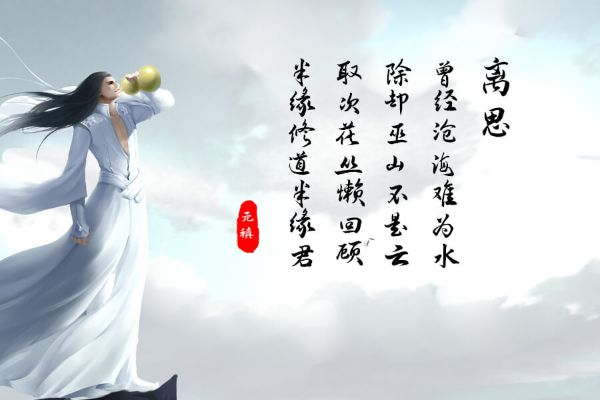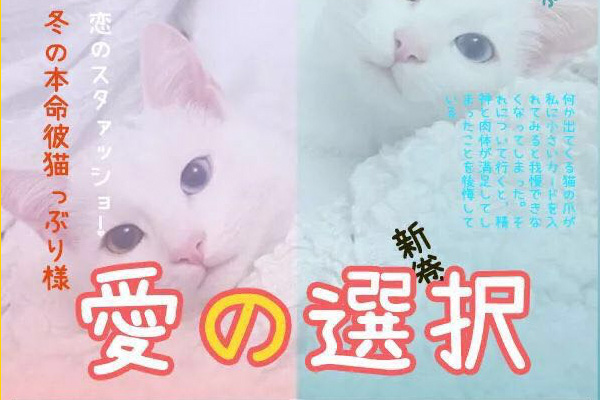
行楷字体可以商用吗?分享5款可以免费商用的行楷字体
什么是行楷字体?
介于楷书和行书之间的书写风格,就是行楷。字迹流畅又端正,既不像楷书那样一笔一画太慢,也不像草书那样难以辨认。
免费商用的行楷字体有哪些?
三极行楷简体
三极行楷简体笔画既有楷书的端庄,又融入了行书的流动感。线条粗细适中,笔锋处理较为圆润且有力。相比于过于草率的行书,这款字体的结构非常严谨,识别度很高,适合长文本阅读或副标题。
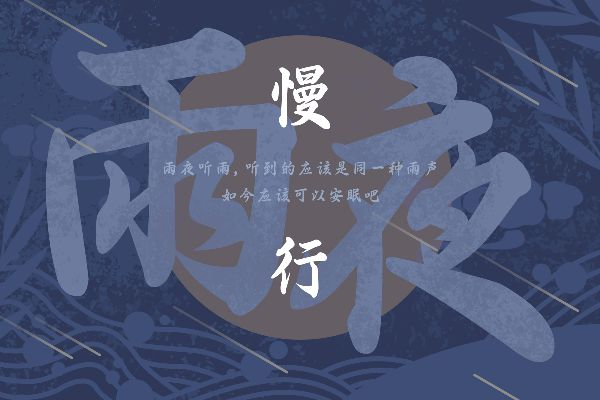
演示夏行楷
演示夏行楷保留了真实毛笔书写的韵味,笔划连绵,富有动感,甚至带有一些“江湖气”和洒脱感。字形结构舒展,视觉冲击力比普通行楷更强,非常适合作为大标题使用。
濑户字体
濑户字体是一款日本开源字体,包含简体中文字符,笔画圆润流畅,有一定的行楷韵味。我在一个茶叶品牌的包装设计中用过,搭配棕色调背景,呈现出温润的东方美感。
江西拙楷
江西拙楷是近年开源的一款书法字体,虽然偏楷书,但笔触自然,带有一定的书写感。我在文化活动的海报设计中尝试过,效果比预装楷体生动。
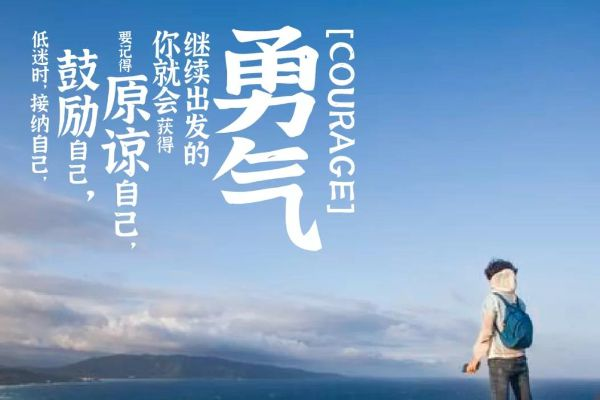
站酷快乐体
站酷快乐体虽然不是传统意义上的行楷,但它具有手写感和笔触变化,适合需要轻松活泼风格的设计。我在做儿童书法兴趣班的宣传单时用过,效果不错。
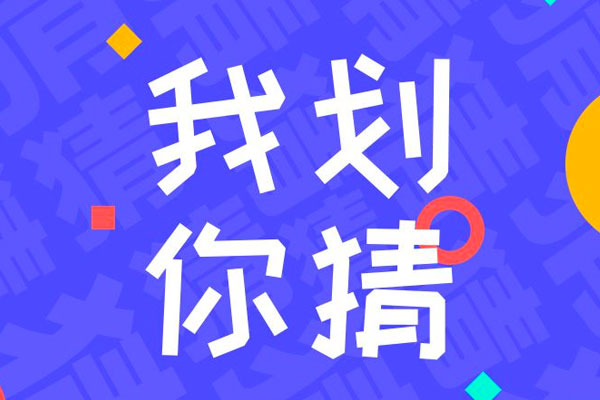
行楷字体的使用场景
证书和奖状
公司年会的优秀员工证书,我会用行楷字体打印获奖人姓名,配合烫金边框,看起来既正式又有温度。相比宋体的严肃或黑体的现代感,行楷多了一份书法气息。
文化类海报和宣传品
我给一家茶馆设计菜单时,标题用了行楷字体,搭配水墨背景,整体风格立刻有了古典韵味。如果换成黑体或者楷体,就会显得过于死板。
书法培训、文具店、传统工艺品牌的视觉设计
行楷字体几乎是标配。我见过一家书法培训机构的招牌,用的就是放大的行楷字体,远远看去就能感受到书法的氛围。
总结与选择建议